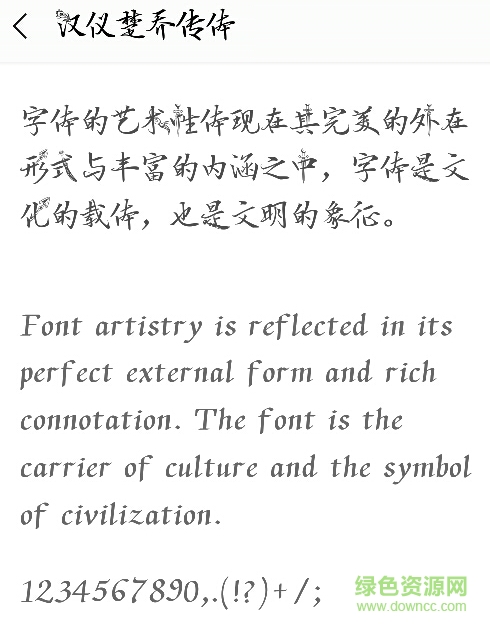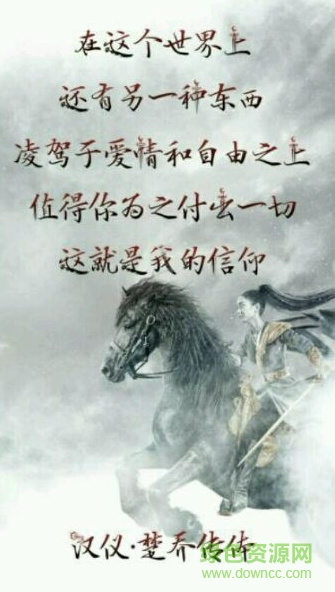
漢儀楚喬字體ttf是在手機(jī)qq上線的同名影視的漢儀字體,字跡干練中帶著一點(diǎn)端莊美,鋒利中透露著溫潤(rùn)的感覺,部分點(diǎn)綴讓字體顯得更加活潑,來(lái)綠色資源網(wǎng)一起體驗(yàn)吧!
漢儀楚喬體出自于熱門電視劇《楚喬傳》,是漢儀字庫(kù)專門為其打造的特色字體,給你影視同步的美好視覺,同時(shí)也可運(yùn)用于海報(bào)設(shè)計(jì)、logo制作等多種行業(yè)!